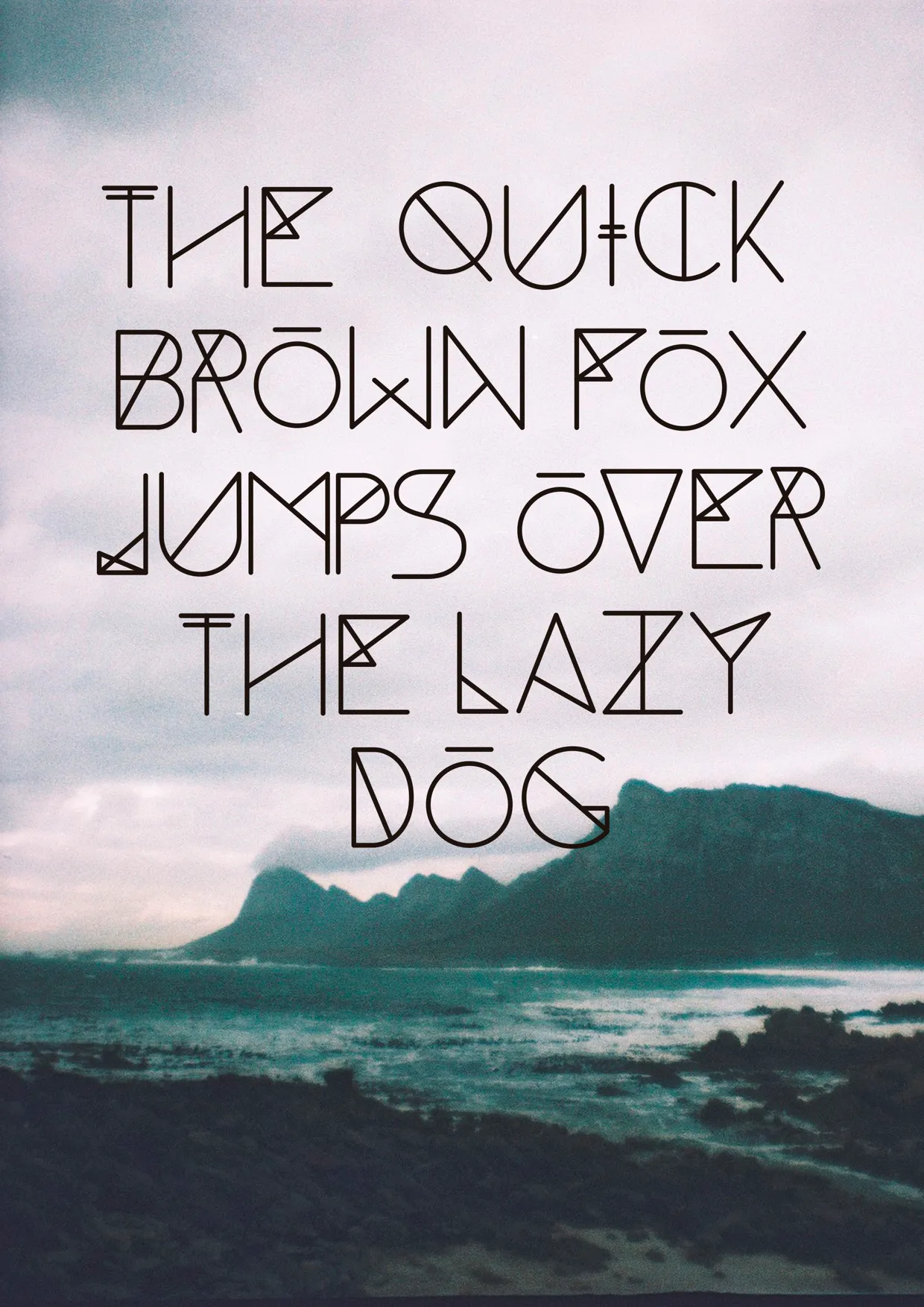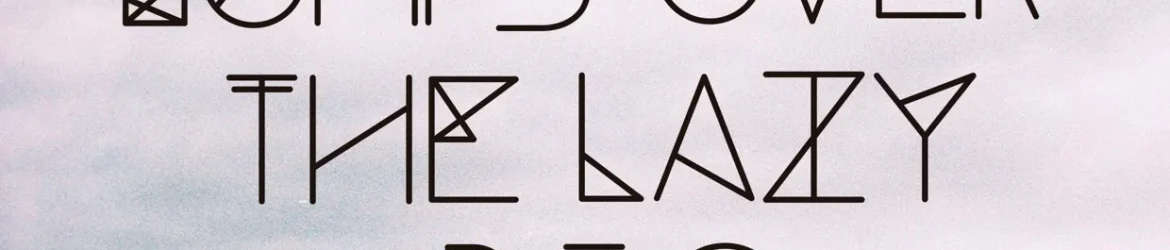
A Parley Typeface é uma fonte simbólica criada pelo designer Hamilton, conhecida por sua estrutura geométrica elegante e seu design futurista. Com linhas retas e formas geométricas definidas, ela oferece um estilo único que combina modernidade com sofisticação. A Parley se destaca especialmente nas categorias de símbolos e icones digitais, pois seu design prático é perfeito para a criação de interfaces de usuário intuitivas, logotipos futuristas e elementos gráficos minimalistas. Suas formas simples permitem que a informação seja transmitida de maneira clara e eficaz em qualquer aplicação digital ou impressa, tornando-a uma escolha ótima para designers buscando um visual único e reconhecível.